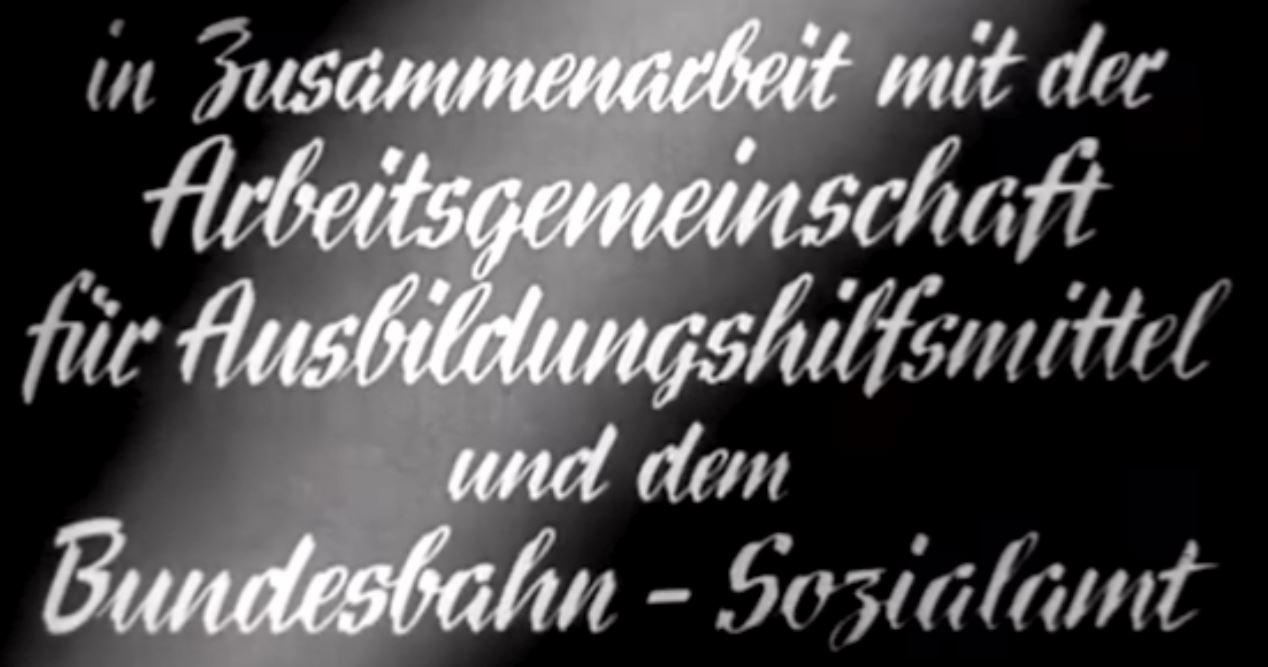
Schriften für alte Plakate Prospekte / Firma Hoffmann Werke
Hallo ich bin neu hier und suche wie so Viele vor mir Schriften. Wie mein Name hier
schon klar zu verstehen gibt tummle ich mich eigentlich in einem anderen Bereich.
Ich habe Spaß am Nachbauen von alten Plakaten und Prospekten bzgl. Vespa und suche hierzu einige Schriften.
Zwei bei dem ich eigentlich schon aufgegeben habe, möchte ich jetzt euerem Schwarmwissen übergeben.
Die Erste (Es gibt doch nur eine) ist ein wenig ausgepinselt ähnlich wie bei der Reporter. Mir hilft es auch schon möglichst
viele Ähnliche zu finden. Bei der Zweiten handelt es sich um das Firmenlogo der Firma Hoffman Werke aus Lintdorf. Die Firma ist leider
seit 1955 Konkurs. Ich bin gespannt ob Ihr mir weiterhelfen könnt. Die Schriften sollten aus den 50er Jahren sein!
Das Problem hierbei: Das wurde alles damals nicht in Blei gesetzt, sondern von einem Grafiker von Hand geschrieben. Solche fast schon mehr wie eine gesetzte Schrift aussehenden Schreibschriften findet man auch in so manchem Film-Vorspann dieser Zeit. So etwas lässt sich eigentlich erst heute einigermaßen vernünftig digital umsetzen, seit man auf OpenType-Funktionen zurückgreifen kann.
Ein weiteres Beispiel einer über mehrere Seiten sehr sauber geschriebener Pinselschrift: